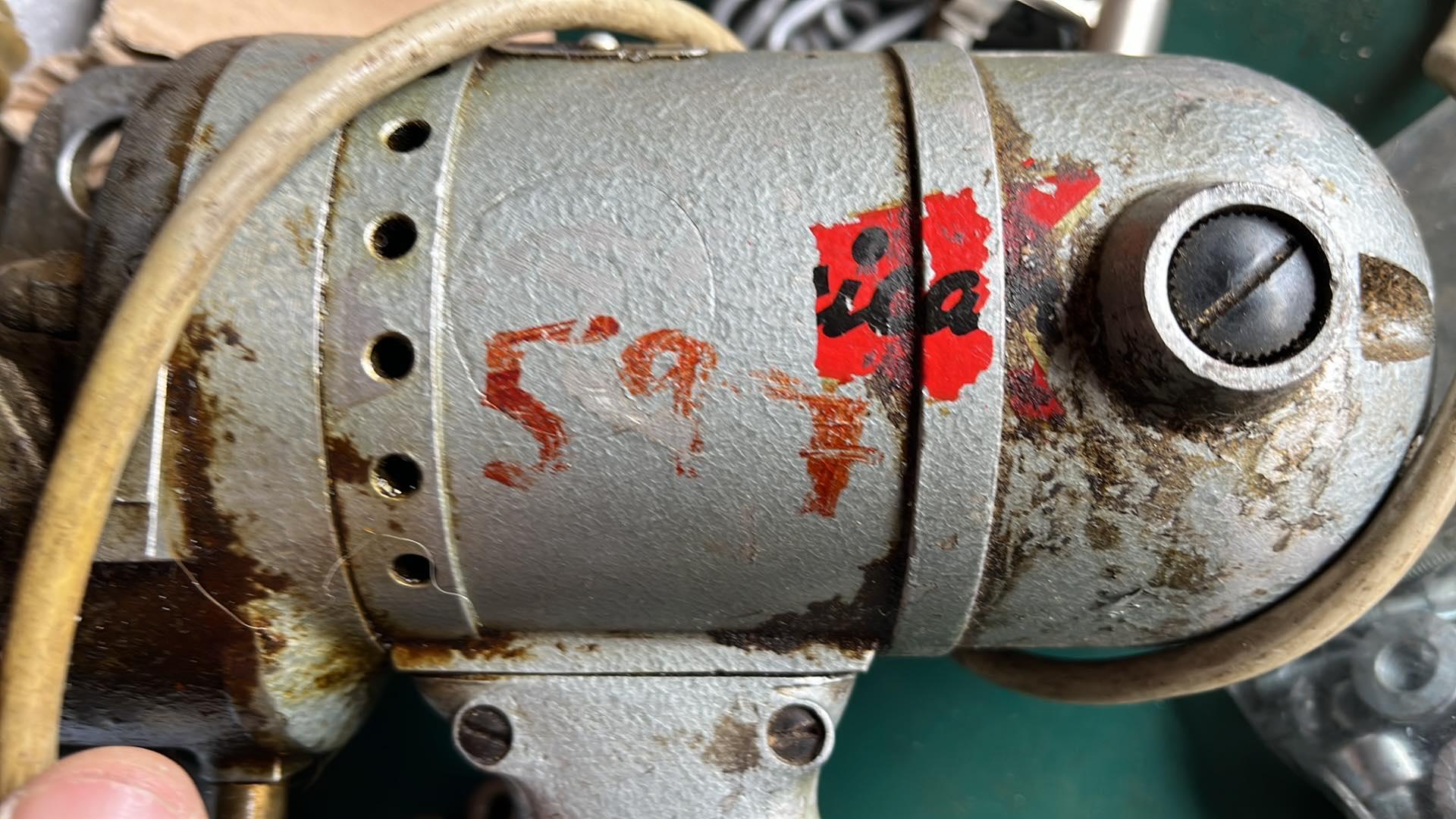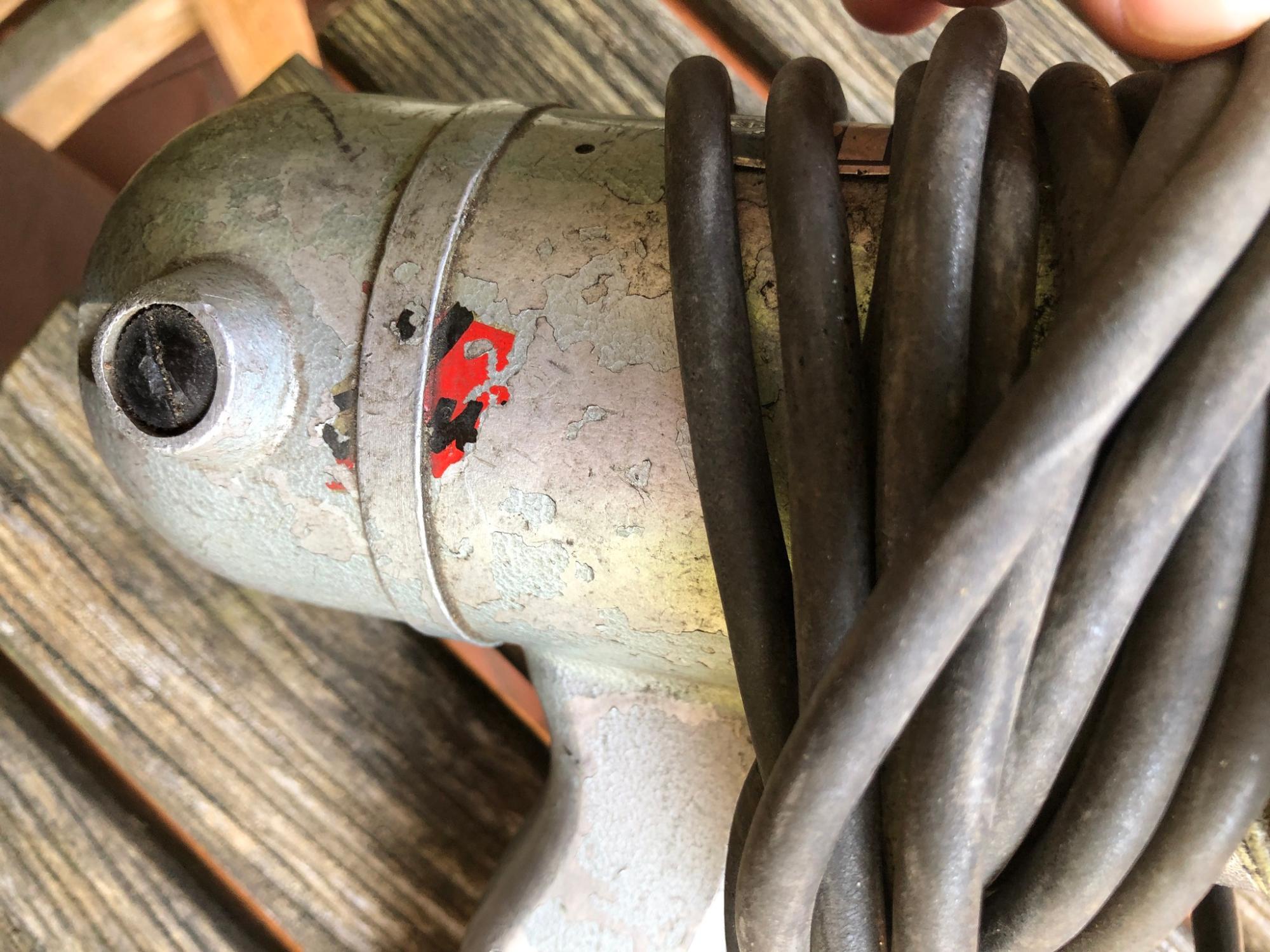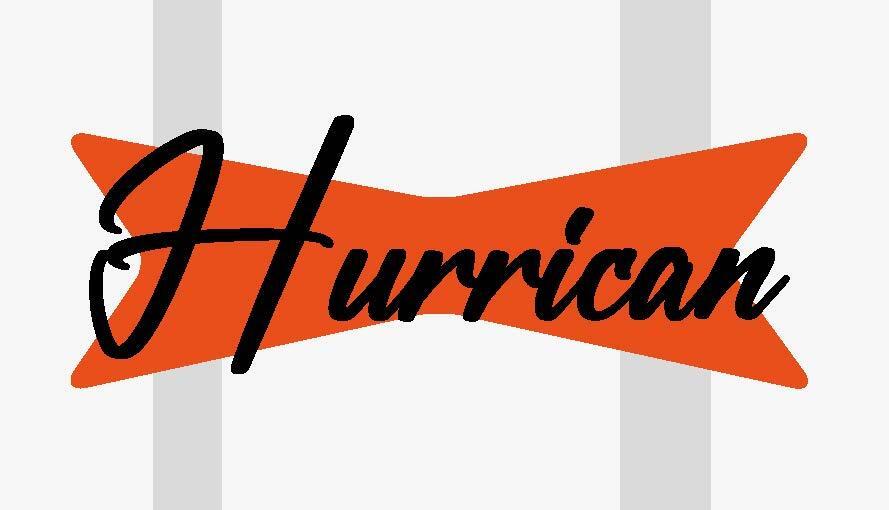
Deutsche Script 50er Jahre
ich bin auf der Suche nach einer zusammenhängenden Schreibschriftart der 50er Jahre.
Es geht dabei um einen Handkompressor von Metabo.
Leider ist der Modellname "Hurrican" nur nach fragmentarisch erhalten.
Mir ist klar, dass es kein Font sein wird, sondern etwas Gezeichnetes.
Ich habe schon einige Schriften, auch aus der Themenseite hier, durchprobiert.
Eubie Script, Belinda und Sugar Crakers waren vom Strich her zu rund oder das H hat nicht gepasst.
Meine Rekonstruktion (Futuristic Stylish) ist auch noch unbefriedigend.
Hat jemand vielleicht eine Idee, welcher Font es besser treffen könnte?
Leider keine Originalabbildung vorhanden.
Bei Metabo wird gesucht, aber es wurde noch nichts gefunden.